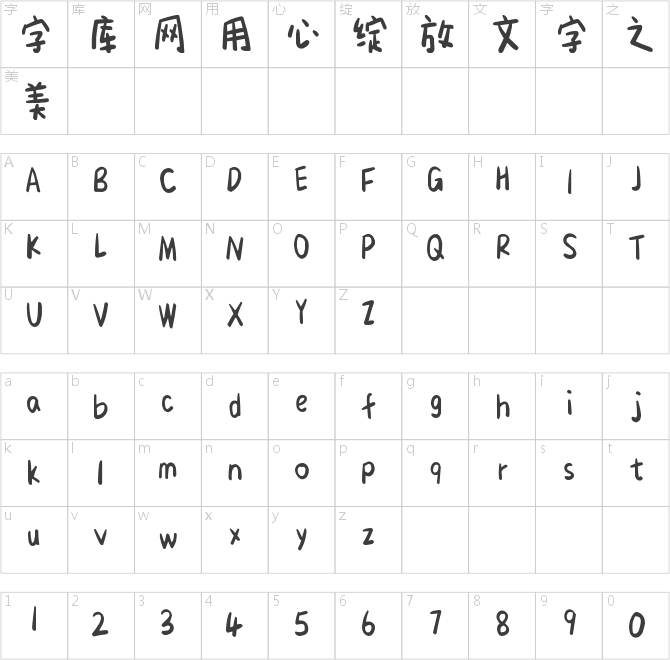
想離你近一點(diǎn)
方正手跡
想離你近一點(diǎn) 字體下載FZSJ-XIANGLNJYD
想離你近一點(diǎn) 字體FZSJ-XIANGLNJYD字庫是一款讓人賞心悅目、百看不厭的中文字體,適合各類廣告和產(chǎn)品包裝設(shè)計(jì)應(yīng)用,字體大小3.45MB,格式為TTF字體,上傳用戶是尼羅河,作者/版權(quán)方為方正手跡